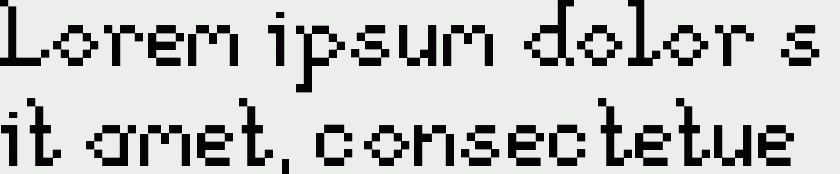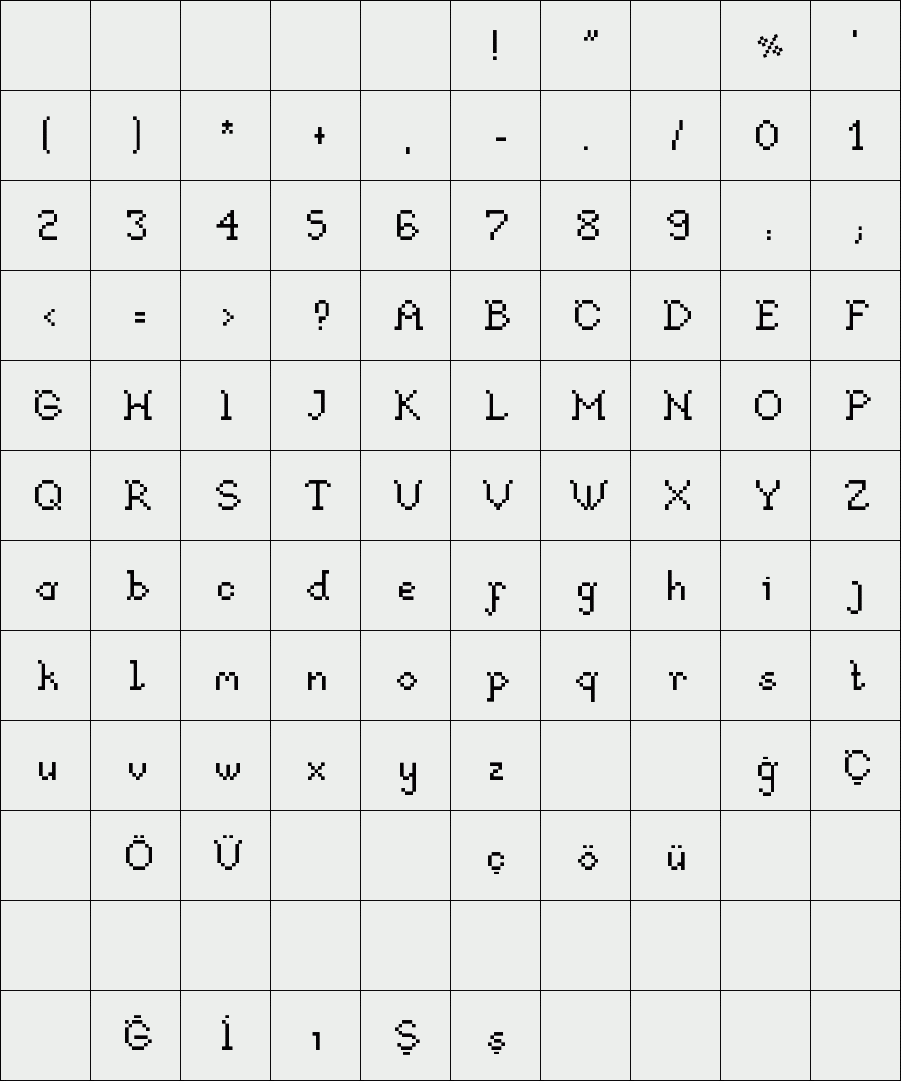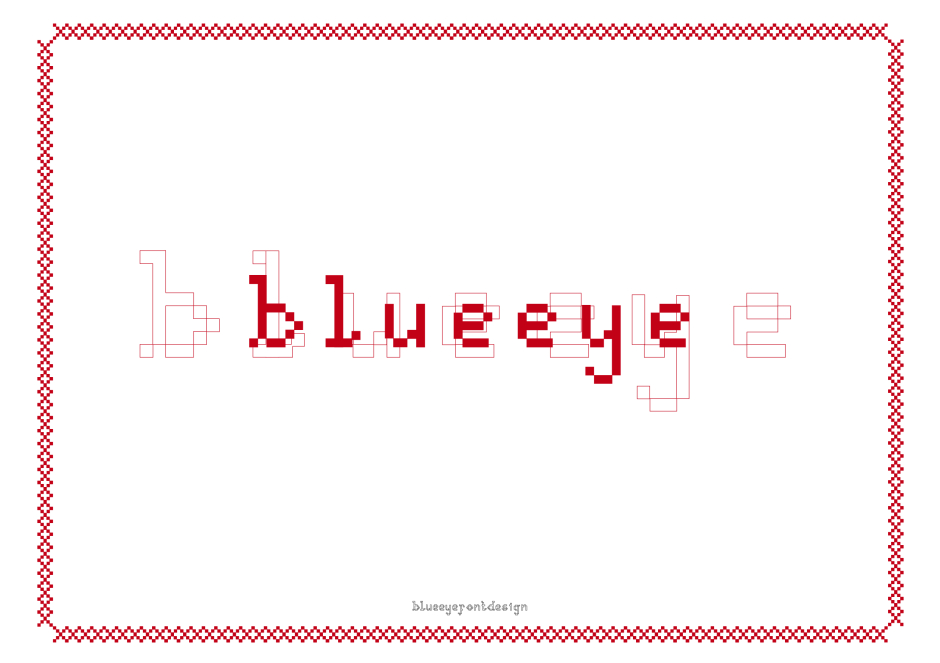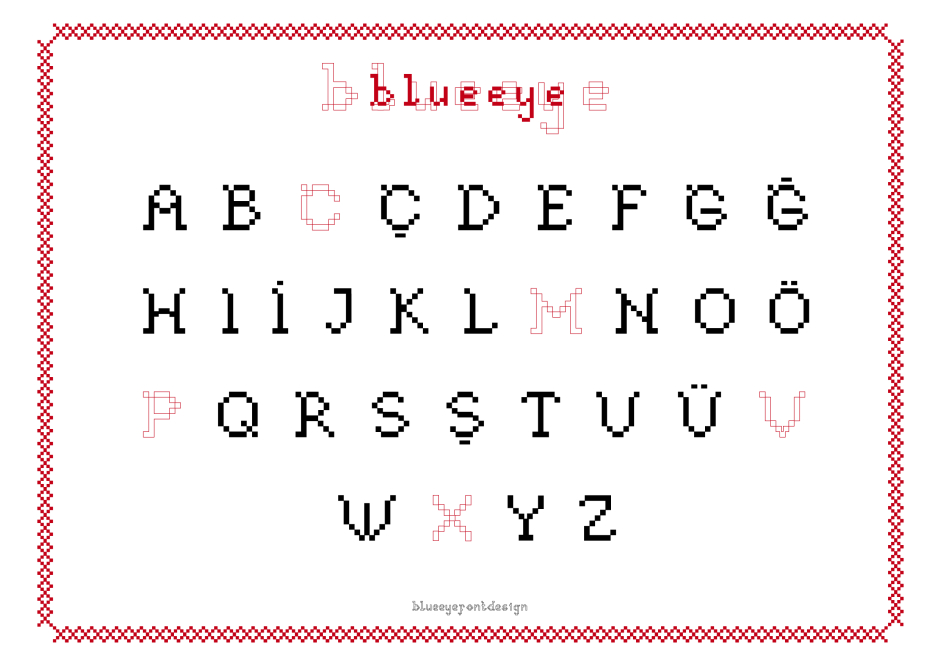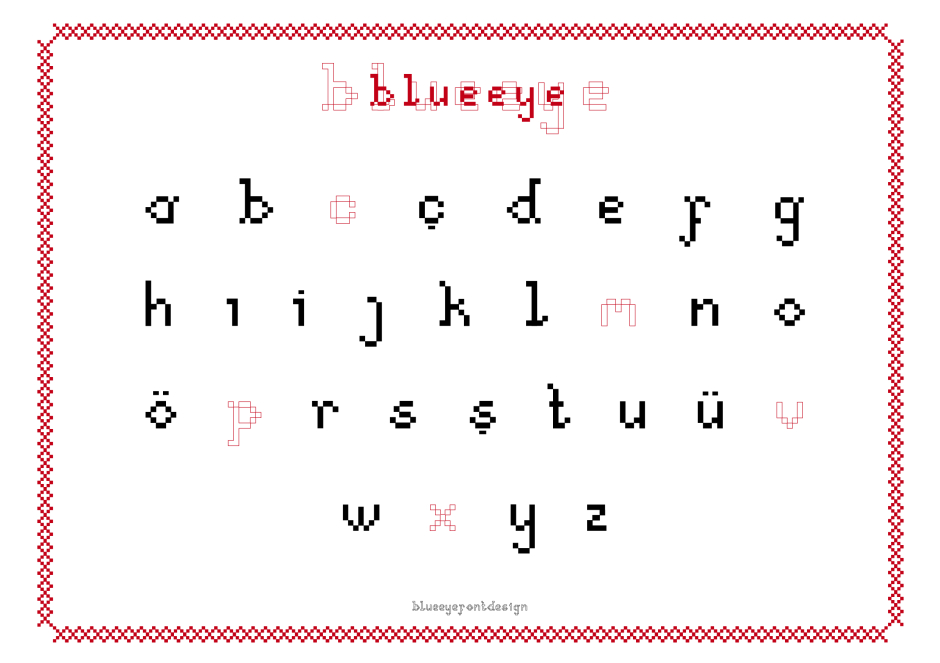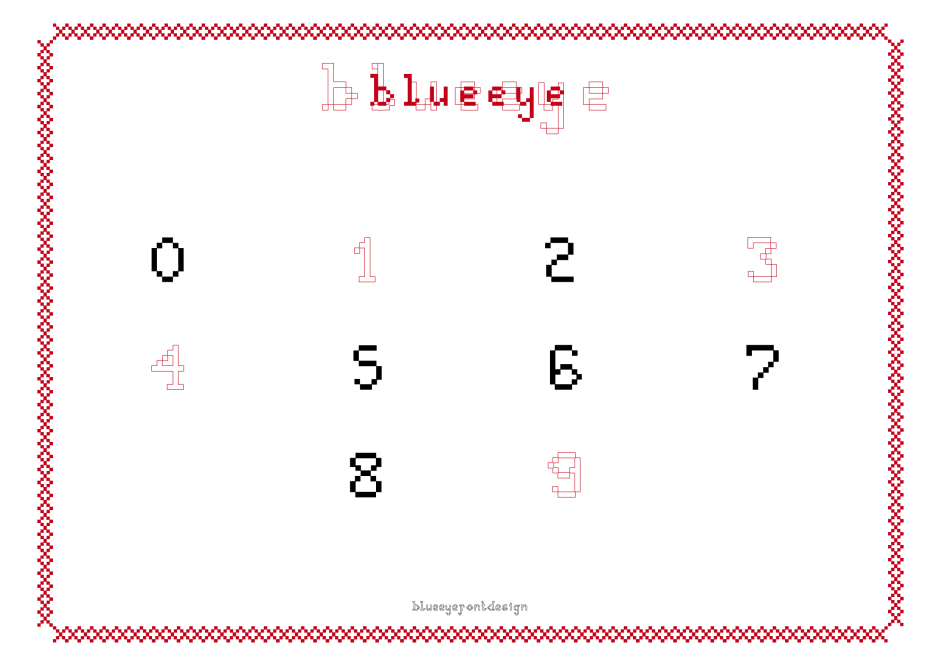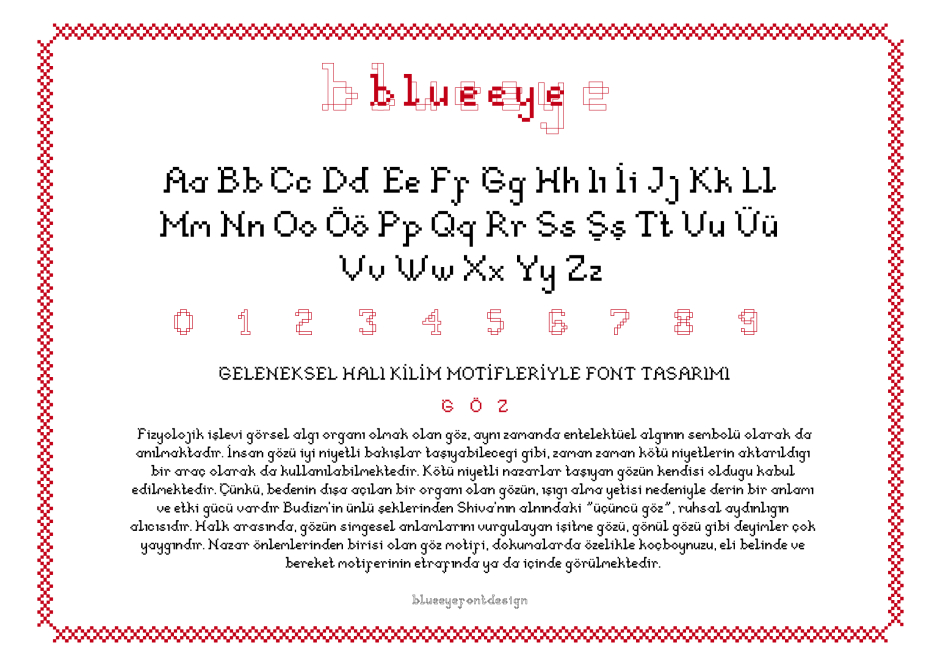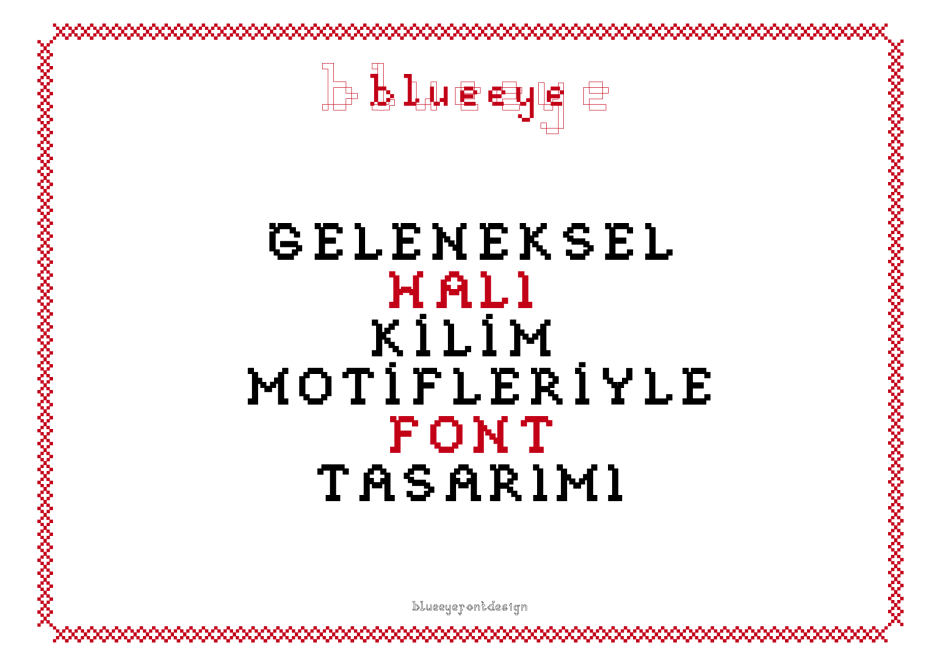
Blueeye
Blueeye font tasarımı geleneksel halı kilim ve motiflerinden yola çıkılarak tasarlanmıştır. Göz motifi baz alınmışve uygulanmıştır.
Designer: Gamze YILDIRIM